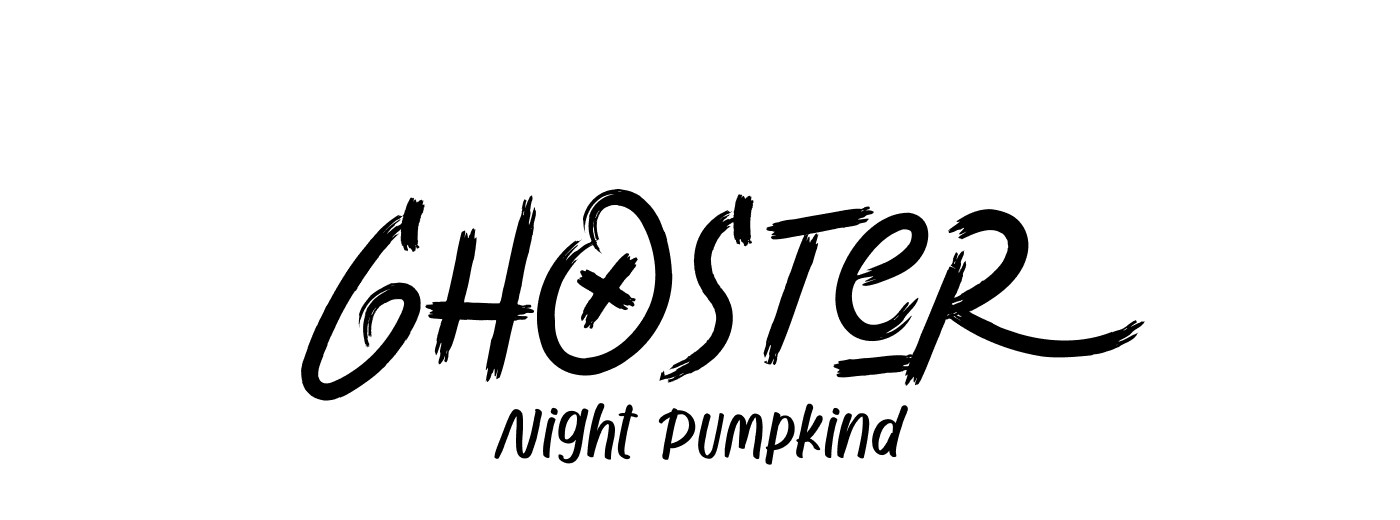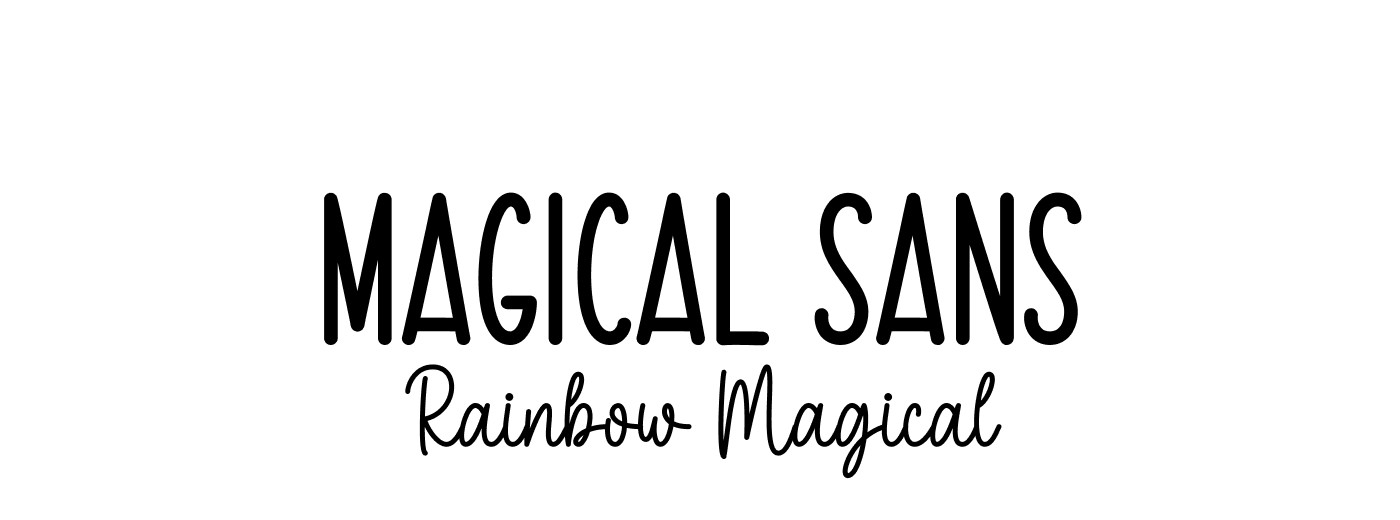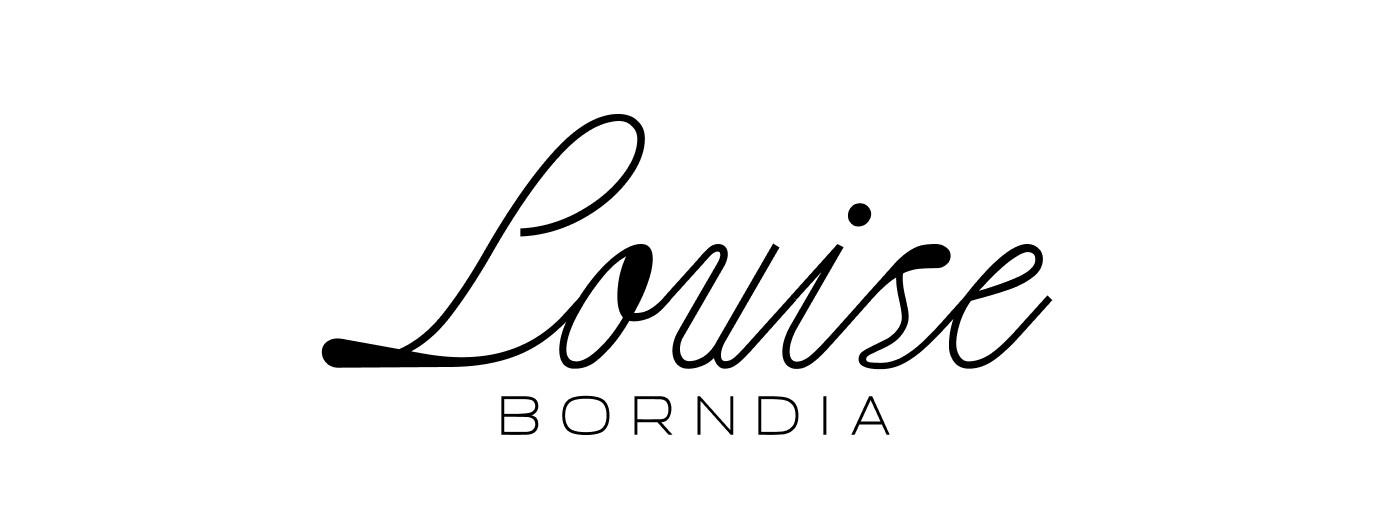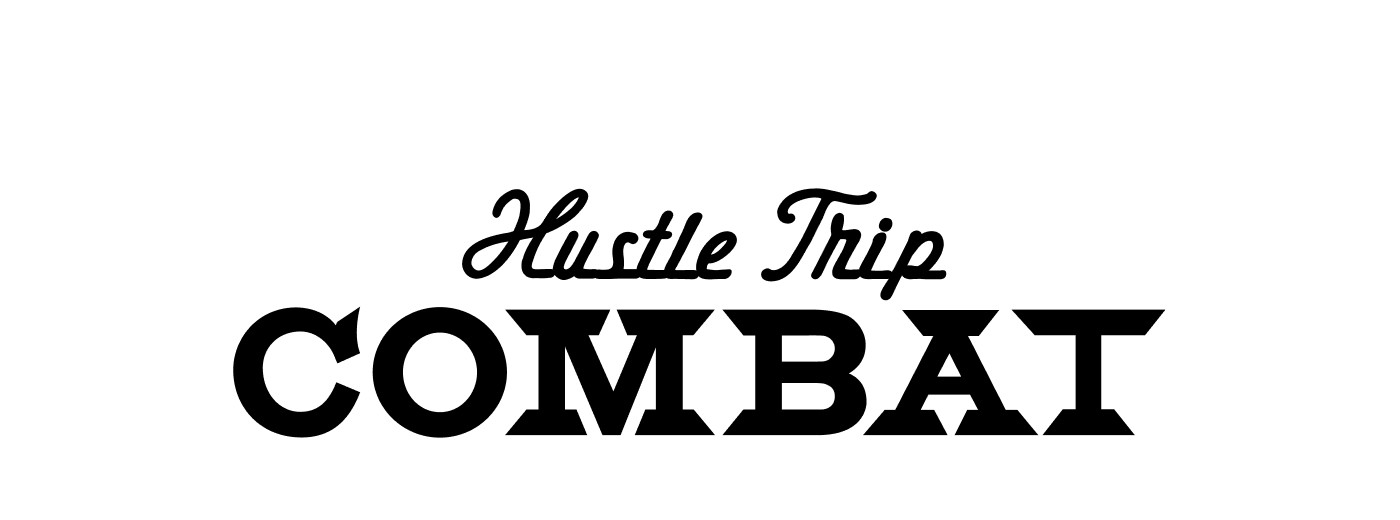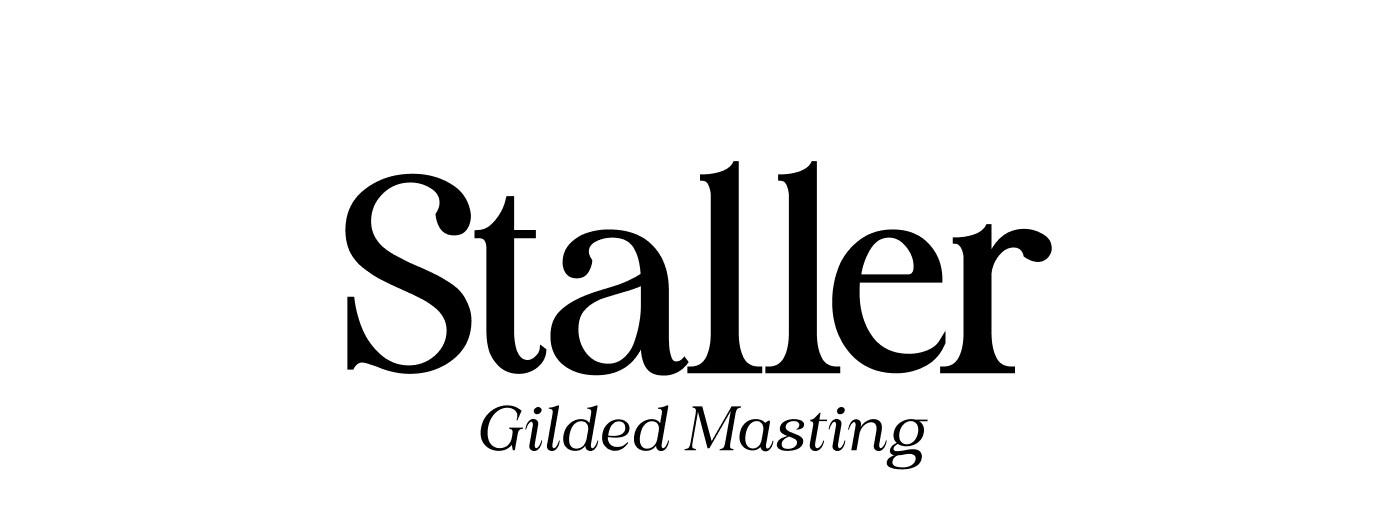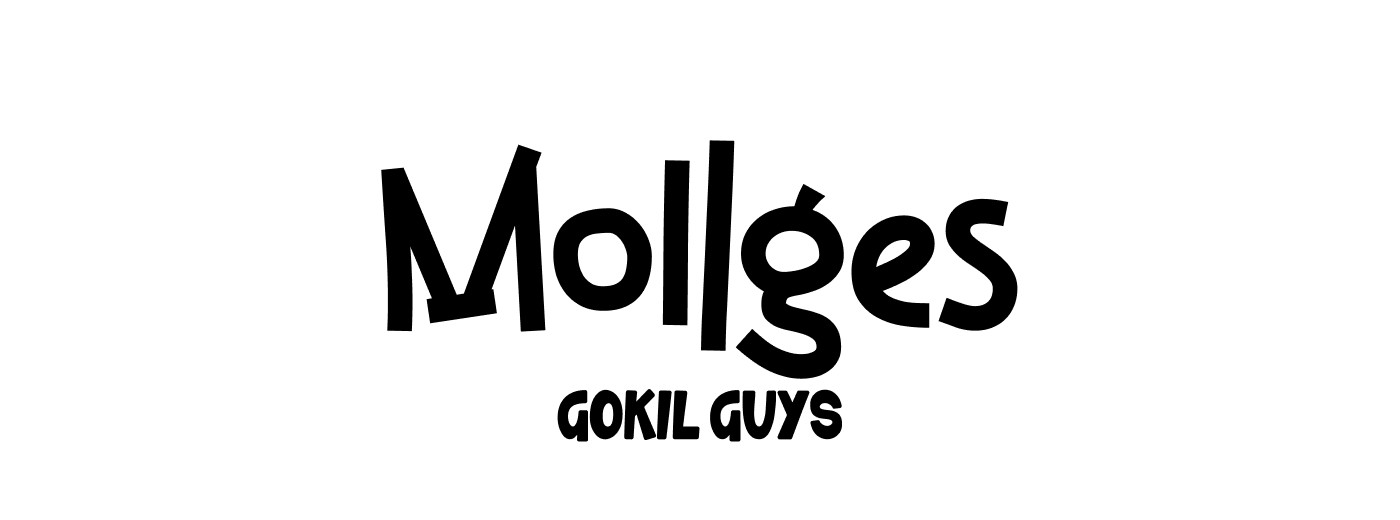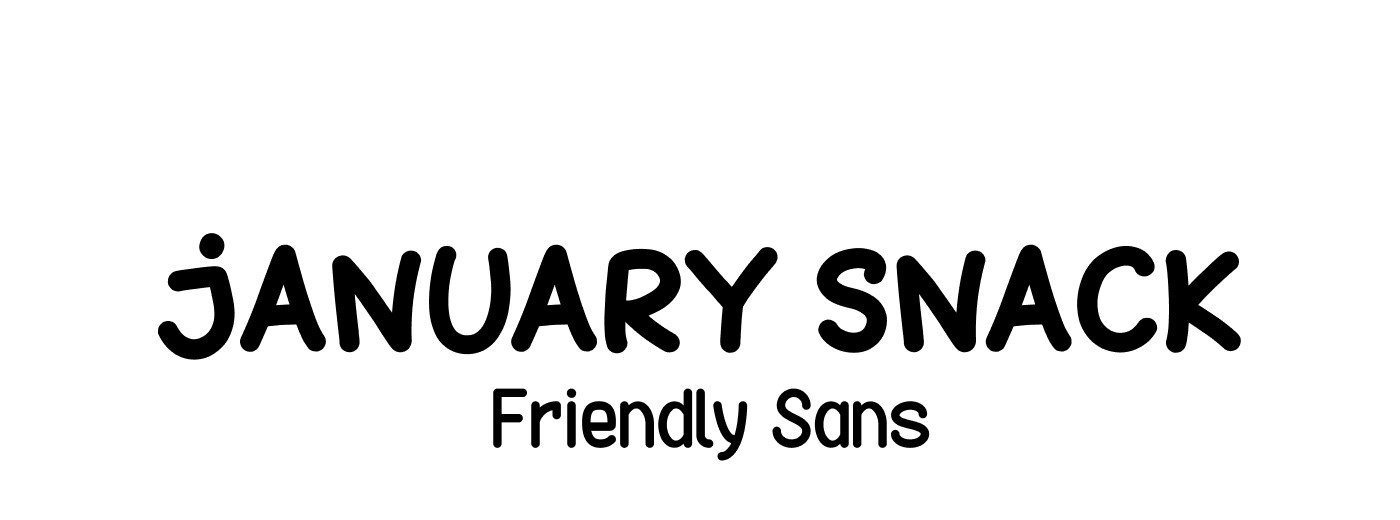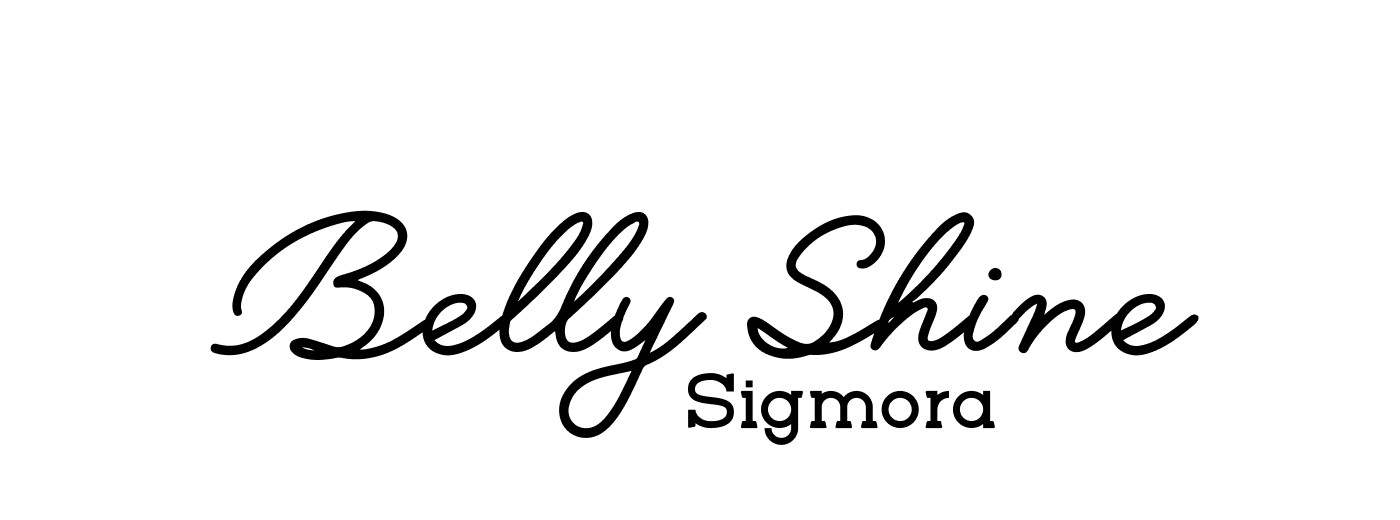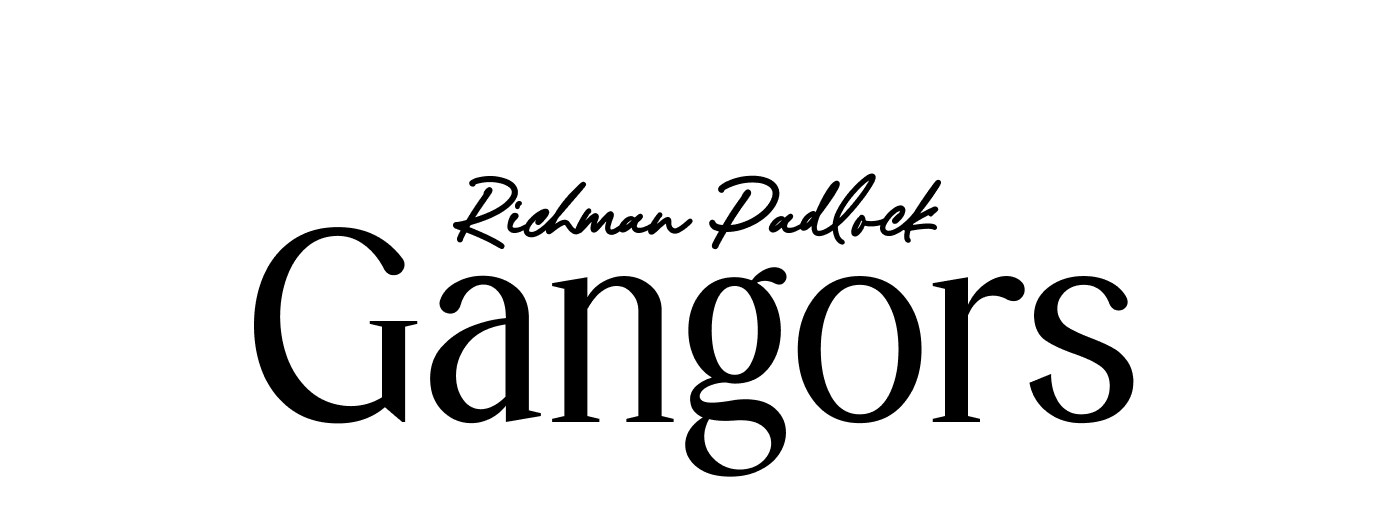
Добро пожаловать в нашу первую коллекцию шрифтовых пар! Здесь представлены уникальные и харизматичные сочетания шрифтов, которые мы подобрали для вас вручную. Это не классические и привычные пары — вы найдете множество акцидентных шрифтов и неожиданных комбинаций, которые прекрасно подойдут для творческих проектов и учебных заданий.
Вдохновляйтесь необычным, и пусть ваши проекты заиграют новыми красками!